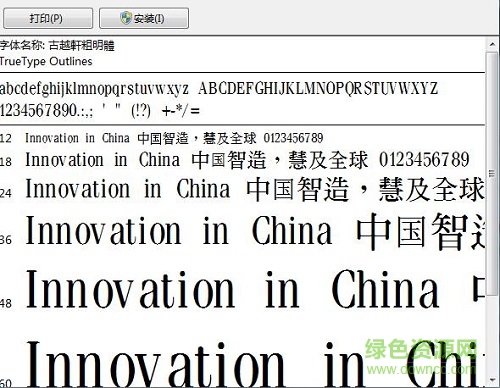
古越軒粗明體繁是一款鮮明醒目的粗體字體,字體自帶加粗特效,非常的醒目,筆畫(huà)如行云流水,非常的順暢,有需要的朋友歡迎下載使用!
古越軒粗明體繁的一款繁體的粗體宋體字體,字體效果比較黑,配上宋體風(fēng)格,給人非常舒服的感覺(jué),適合應(yīng)用于廣告設(shè)計(jì)、名片設(shè)計(jì)、包裝印刷、產(chǎn)品設(shè)計(jì)等應(yīng)用。